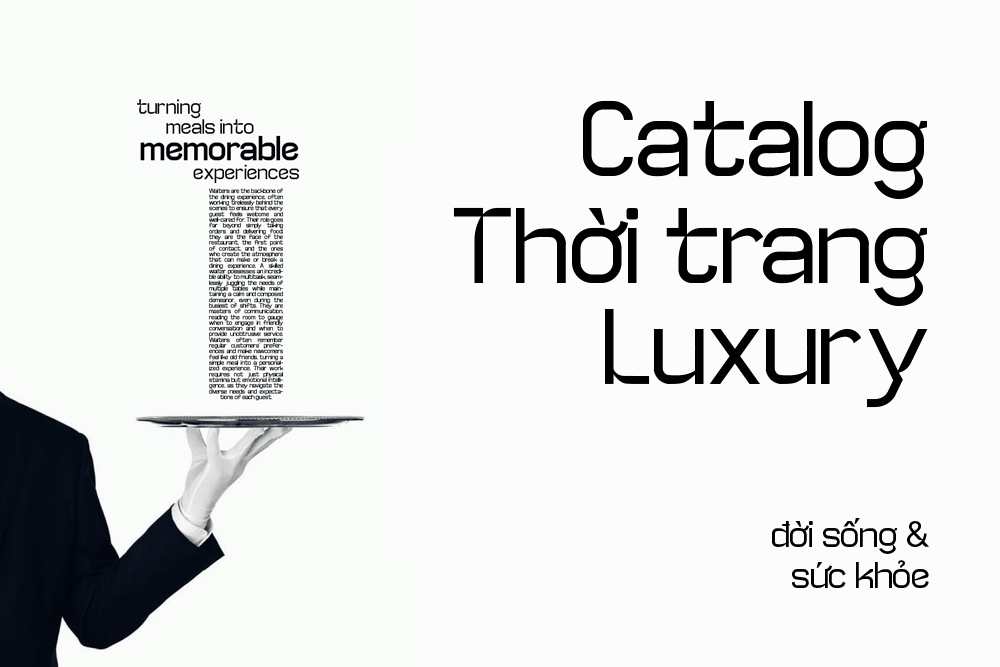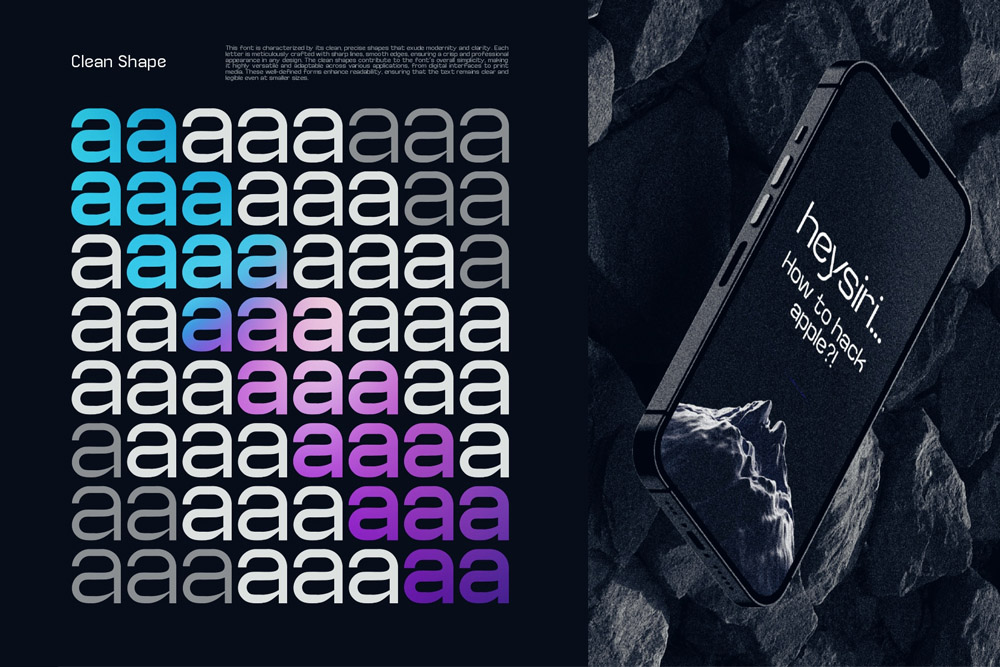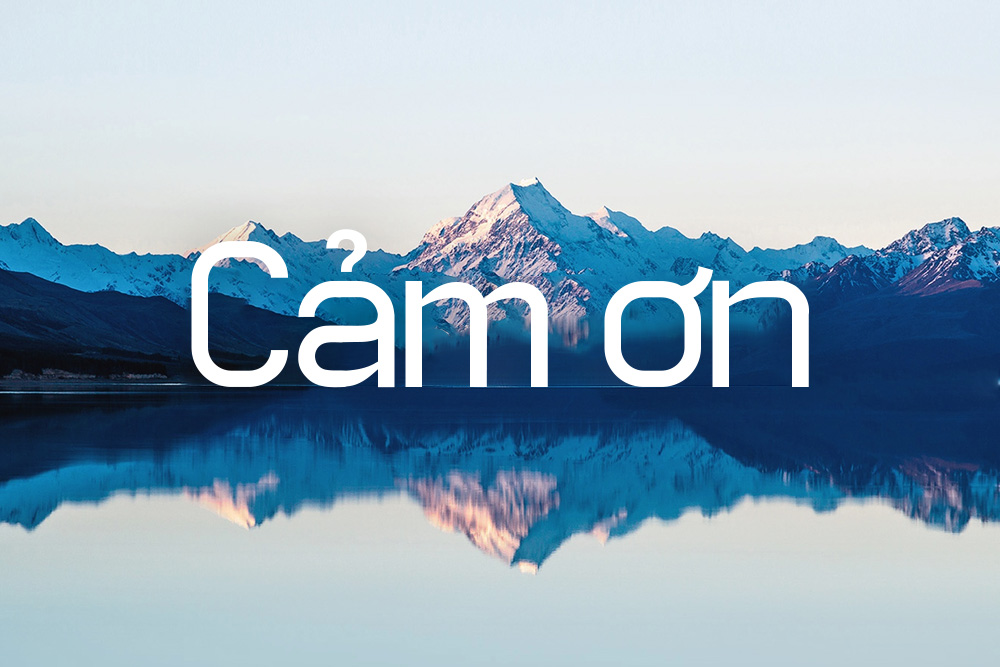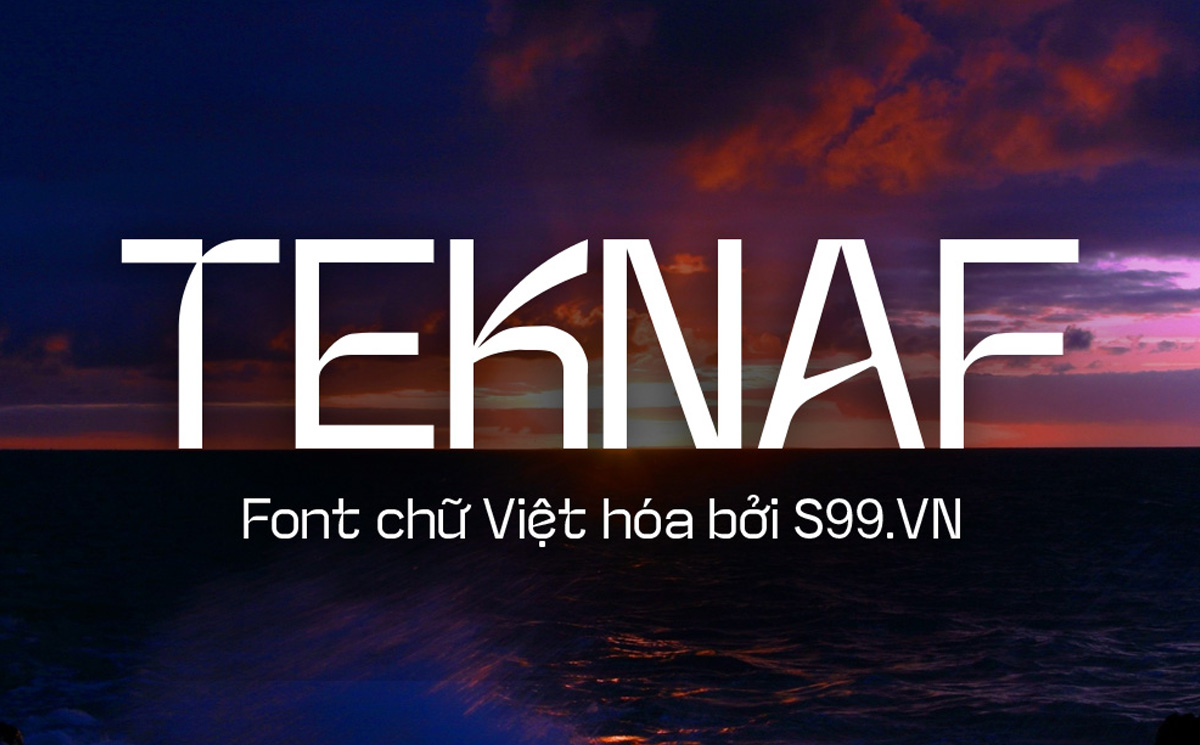
Font chữ TH Teknaf sans-serif hiện đại, tối giản và mạnh mẽ - Font Việt hóa
TH Teknaf là phiên bản Việt hóa của font chữ Teknaf do NazmulsDesign phát hành. Được Việt hóa và tối ưu bởi đội ngũ S99.VN, TH Teknaf hỗ trợ đầy đủ tiếng Việt với hệ thống dấu và ký tự chuẩn xác – đảm bảo tính thẩm mỹ và tương thích cao cho các nhà thiết kế Việt.
Về phong cách, TH Teknaf thuộc nhóm font chữ sans-serif với kết cấu hình học hiện đại, mang đường nét sắc sảo, vuông vức nhưng vẫn mềm mại ở những chi tiết bo cong nhẹ nhàng. Sự tối giản trong cấu trúc giúp font dễ đọc, gọn gàng và phù hợp với xu hướng thiết kế số hiện đại – từ giao diện website, ứng dụng, cho đến nhận diện thương hiệu.
Với tỷ lệ ký tự được cân đối cẩn thận, TH Teknaf tạo cảm giác chuyên nghiệp và mạnh mẽ. Các đường nét được giữ đều đặn, chiều cao đồng nhất và khoảng cách chữ hài hòa giúp tối ưu khả năng trình bày trong mọi kích thước, từ tiêu đề lớn cho đến nội dung văn bản nhỏ.
Nếu bạn đang tìm kiếm một font chữ sans-serif gọn gàng, có phong cách rõ ràng và hỗ trợ tiếng Việt đầy đủ, TH Teknaf chắc chắn sẽ là lựa chọn lý tưởng trong bộ sưu tập font chuyên nghiệp của bạn.